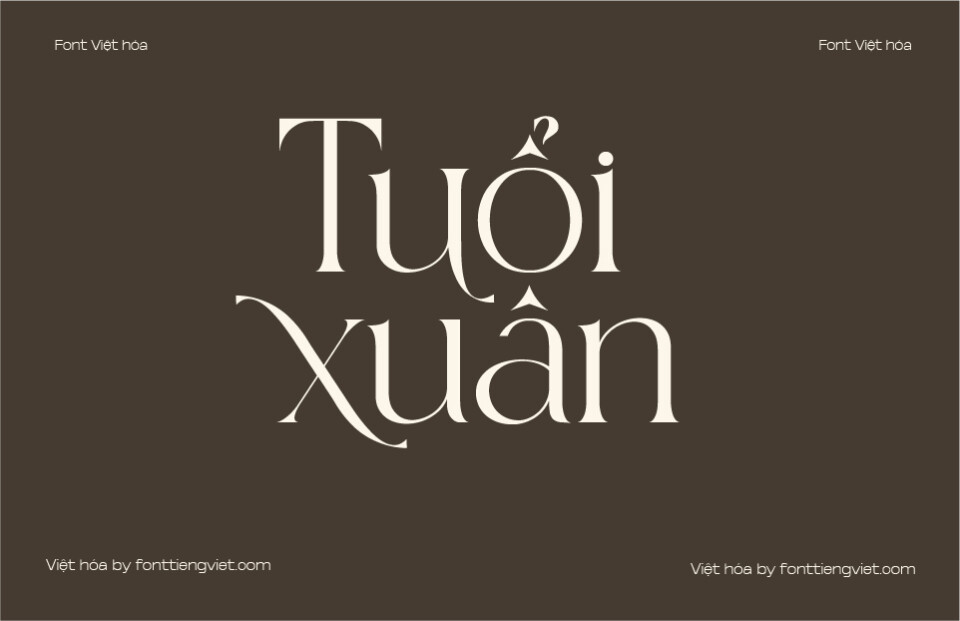
Font Việt hóa 1FTV VIP Dagine
Font Việt hóa 1FTV VIP Dagine – Bộ Font Chữ Sang Trọng Và Đẳng Cấp Cho Thiết Kế Chuyên Nghiệp
Giới thiệu về bộ Font Việt hóa 1FTV VIP Dagine trong thiết kế hiện đại
Trong thế giới đồ họa ngày càng phát triển, việc lựa chọn một bộ Font Miễn Phí chất lượng luôn là ưu tiên hàng đầu của các nhà thiết kế chuyên nghiệp lẫn các bạn học sinh đang làm quen với mỹ thuật số. Trong đó, Font Việt hóa 1FTV VIP Dagine nổi lên như một hiện tượng nhờ sự kết hợp hoàn hảo giữa nét hiện đại và phong cách sang trọng. Đây là phiên bản được tinh chỉnh kỹ lưỡng về dấu tiếng Việt, giúp người dùng loại bỏ hoàn toàn nỗi lo lỗi hiển thị khi soạn thảo văn bản hay làm tiêu đề cho các ấn phẩm truyền thông tại Việt Nam.
Sự xuất hiện của 1FTV VIP Dagine mang đến một làn gió mới cho kho tàng font chữ Việt hóa. Bộ font này không chỉ dừng lại ở tính thẩm mỹ mà còn đảm bảo được độ sắc nét trên nhiều nền tảng hiển thị khác nhau. Với cấu trúc các nét thanh mảnh nhưng chắc chắn, nó tạo nên cảm giác tin cậy và chuyên nghiệp cho bất kỳ bản thiết kế nào sử dụng đến. Đối với các bạn học sinh, sinh viên, việc tiếp cận với những bộ font chất lượng như thế này sẽ giúp các em nâng cao tư duy thẩm mỹ và tạo ra những bài thuyết trình hay báo cáo học tập bắt mắt hơn bao giờ hết.
Những đặc điểm nổi bật của Font Việt hóa 1FTV VIP Dagine
Cấu trúc hình học hài hòa và tinh tế
Điểm thu hút nhất của Font Việt hóa 1FTV VIP Dagine chính là cấu trúc hình học cân đối. Từng đường cong và nét thẳng được tính toán tỉ mỉ để tạo ra sự hài hòa tổng thể. Điều này giúp bộ font giữ được sự rõ ràng ngay cả khi sử dụng ở kích thước nhỏ. Các dấu tiếng Việt như dấu huyền, dấu sắc hay dấu hỏi được đặt ở vị trí hợp lý, không làm phá vỡ cấu trúc nguyên bản của ký tự gốc, giúp văn bản trở nên dễ đọc và có tính nghệ thuật cao.
Ứng dụng đa dạng trong nhiều lĩnh vực sáng tạo
Nhờ vẻ ngoài đẳng cấp, 1FTV VIP Dagine thường xuyên được các chuyên gia lựa chọn để thiết kế bộ nhận diện thương hiệu, bìa sách hoặc các poster quảng cáo cao cấp. Trong môi trường học đường, giáo viên có thể dùng font chữ này để thiết kế các chứng chỉ, bằng khen hoặc tài liệu giảng dạy sinh động. Tính linh hoạt của nó cho phép người dùng tự do sáng tạo mà không bị gò bó bởi các quy tắc thiết kế truyền thống khô khan.
Hướng dẫn sử dụng và tối ưu hóa trải nghiệm người dùng
Để phát huy tối đa vẻ đẹp của 1FTV VIP Dagine, bạn nên kết hợp nó với những bộ font không chân (sans-serif) đơn giản khác. Việc tạo ra sự tương phản giữa tiêu đề sử dụng 1FTV VIP Dagine và nội dung văn bản bằng một font chữ cơ bản sẽ giúp người xem dễ dàng tập trung vào thông điệp quan trọng nhất. Đừng quên điều chỉnh khoảng cách giữa các chữ cái (kerning) để tạo ra sự thông thoáng cho bản thiết kế của mình.